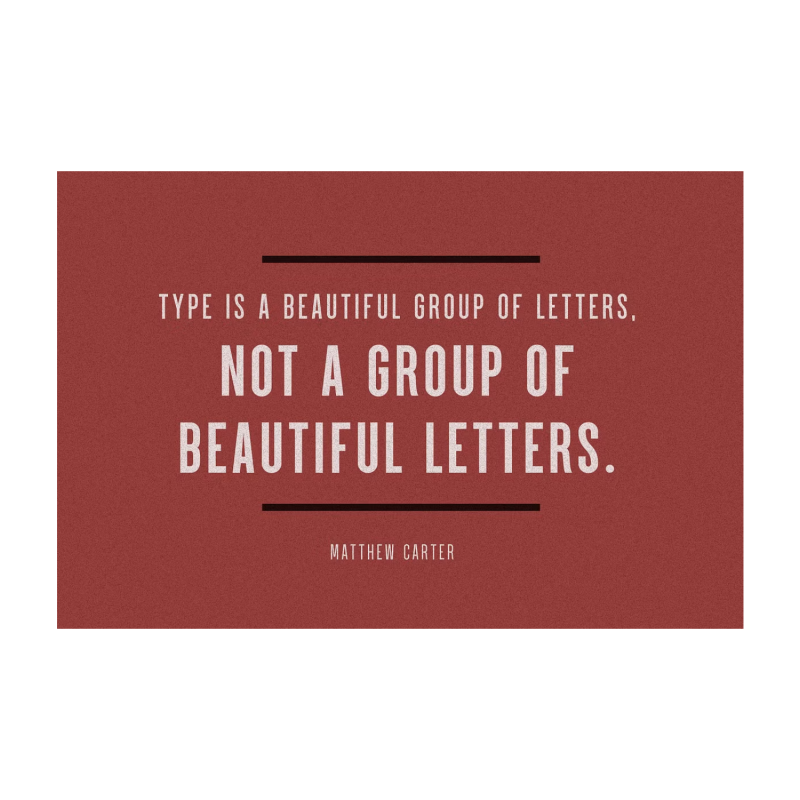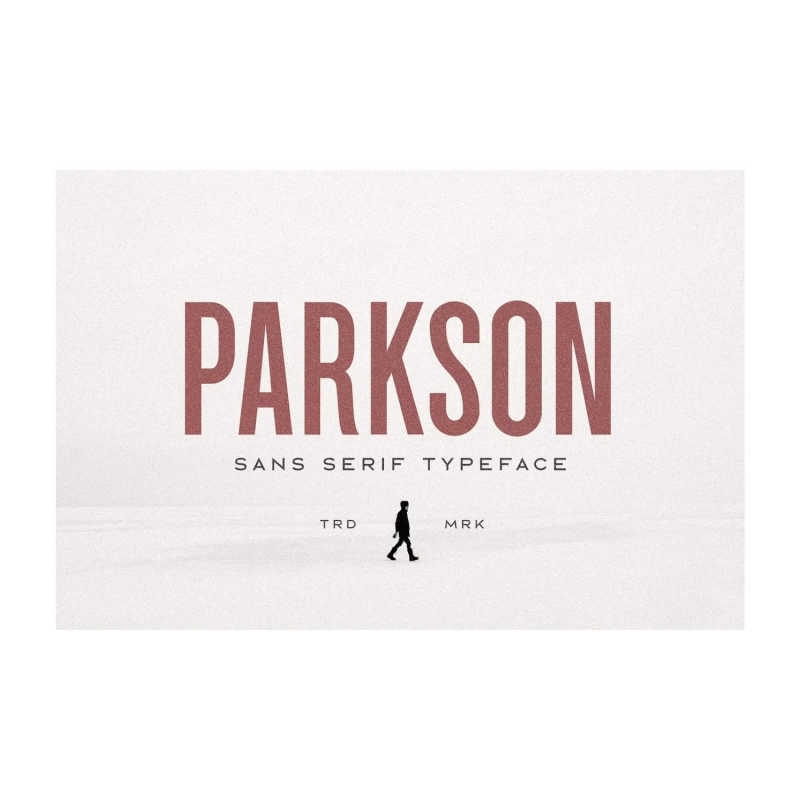
باركسون بلا شريف - 18 الخطوط
مستوحاة من الخطوط الغريبة في القرن 19 ، Parkson هو محرف طويل القامة sans serif من 7 أوزان جنبا إلى جنب مع مائل والعديد من الإصدارات المخططة. يهدف الخط المعاصر إلى أن يكون أحد أفضل مجموعات الخطوط المكثفة في العالم. تم تصميمه للحصول على وضوح مثالي ، ومظهره الهندسي النظيف مثالي لأنواع الشعارات والرؤوس والعناوين والكتيبات.
مع Parkson ، تحصل على ثمانية عشر خطا لمجموعة واسعة من التنوع. يتكون كل خط من 221 حرفا رسوميا لتغطية مجموعة واسعة من دعم اللغة ، بما في ذلك جميع اللغات في أوروبا الغربية.